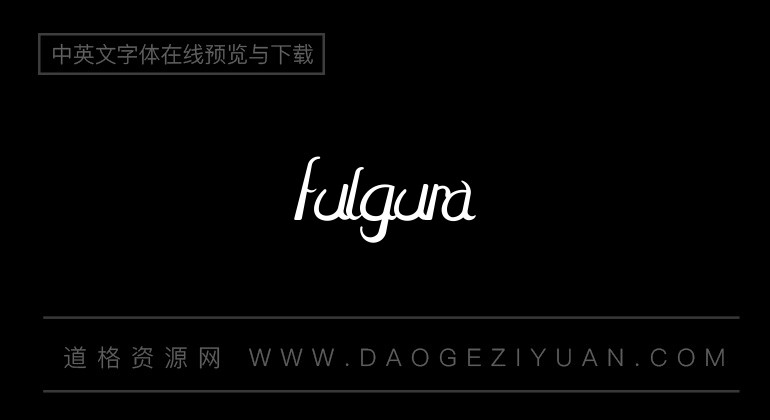
Fulgura
Fulgura 字体是一款简约而精致的字体,它具有明显的现代感,适合用于标题、抬头、标识等场景。Fulgura 字体采用细腻的线条和优雅的字形,在细节上让人眼前一亮,具有强烈的视觉冲击力,可以很好地展示出品牌的特色和个性。它的灵活性和多样性使它可以满足多种不同的设计需求,是一款非常出色的字体。
Fulgura是一款非常不错的手写艺术字体,具有很好的视觉感,适合于文化类的宣传设计、商业类品牌的广告和产品包装设计以及个性化文字排版等较多场景。